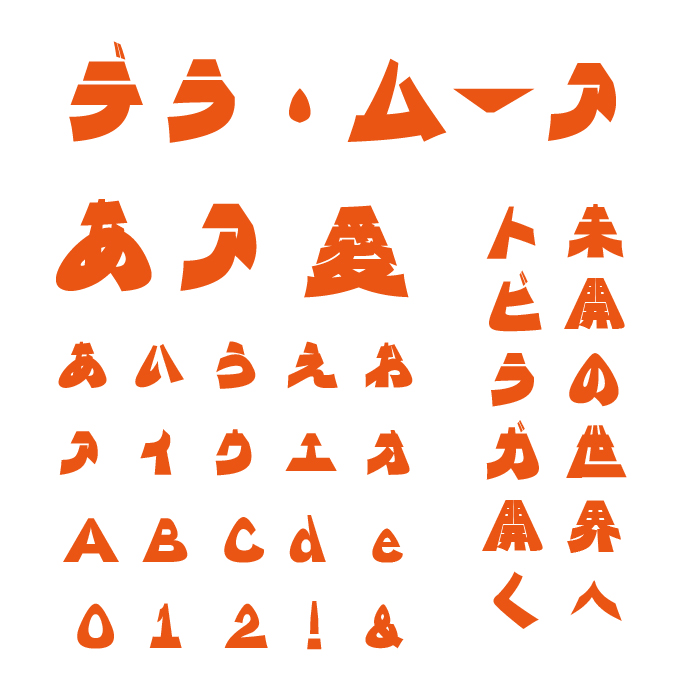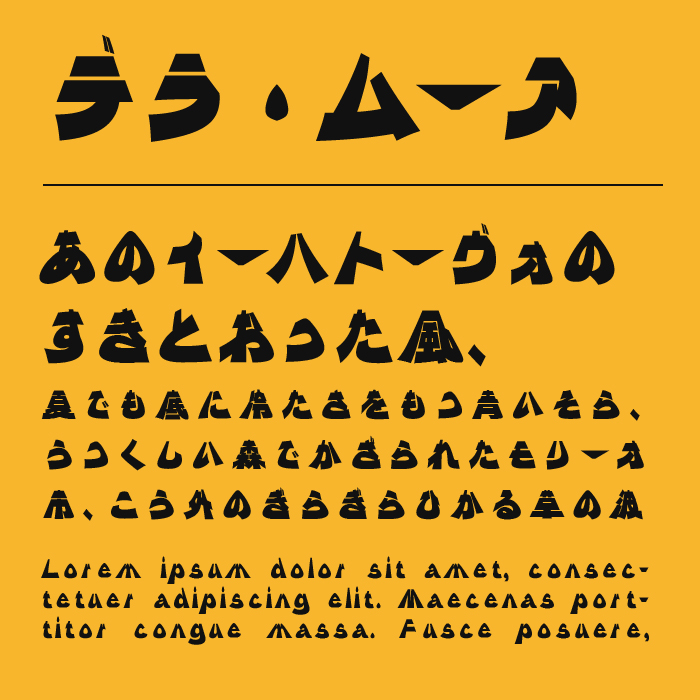
デラ・ムーアフォントは、デラゴシックフォントをベースに使い、切り絵のようなシャープな形が特徴の、存在感の強いデザインフォントです。画の端が三角に切り取られたようなデザインで、一文字ごとに個性がはっきり出ています。
異国感のある雰囲気を持っているので、エスニック料理のメニューや冒険をテーマにしたイベントのポスターなどにおすすめです。文字だけでも独特の世界観が伝わるので、短いフレーズを強調する使い方が合います。
長い文章には向かないフォントですが、3〜10文字程度の短いキャッチコピーに使うととても効果的です。